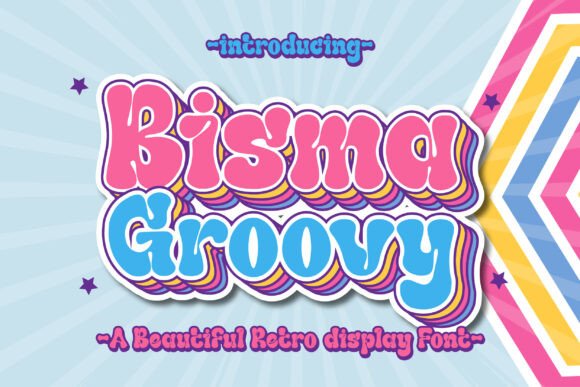
Bisma Groovy
Bisma Groovy – A Fonte Retro que Transforma Seu Design
Se você busca uma tipografia vintage que una carisma, vibração e autenticidade, Bisma Groovy é a escolha ideal. Inspirada na era hippie, essa fonte traz à tona a espírito livre dos anos 60‑70, garantindo projetos cheios de personalidade e energia.
- Estilo retro‑inspirado: formas arredondadas e linhas fluidas que remetem ao movimento cultural da década de 70.
- Versatilidade criativa: funciona perfeitamente em blogs, logos, identidade visual, anúncios, convites e cartões de felicitação.
- Toque de autenticidade: cada letra carrega um charme “hand‑crafted”, ideal para projetos que desejam transmitir nostalgia e originalidade.
- Alta legibilidade: apesar do visual descontraído, a fonte mantém clareza em tamanhos pequenos, facilitando sua aplicação em textos e headings.
Onde Usar Bisma Groovy?
Esta fonte se destaca em diversas áreas, como:
- Blogs e sites: títulos e chamadas que desejam capturar a atenção do leitor com um ar retro.
- Branding e logotipos: marcas que buscam transmitir criatividade, liberdade e um toque vintage.
- Campanhas publicitárias: anúncios que precisam evocar memórias de uma época mais descontraída.
- Convites e cartões: eventos temáticos, festas de anos 70, casamentos boho ou celebrações especiais.
- Materiais impressos: agendas, capas de álbum de fotos, flyers e embalagens com design diferenciado.
Benefícios de Escolher Bisma Groovy
Ao incorporar Bisma Groovy ao seu projeto, você garante:
- Um visual único que se destaca em meio à tipografia padrão.
- Conexão emocional com o público ao despertar nostalgia e boas memórias.
- Facilidade de uso em diferentes plataformas, sem comprometer a qualidade.
- Um toque de charme vintage que eleva a percepção de valor da sua marca.
Seja para dar vida a um blog descontraído, criar um logotipo memorável ou produzir convites cheios de personalidade, Bisma Groovy oferece a combinação perfeita de estilo retro e versatilidade moderna. Experimente esta fonte e veja seu design alcançar um novo patamar, cheio de vibração e charme da era hippie.